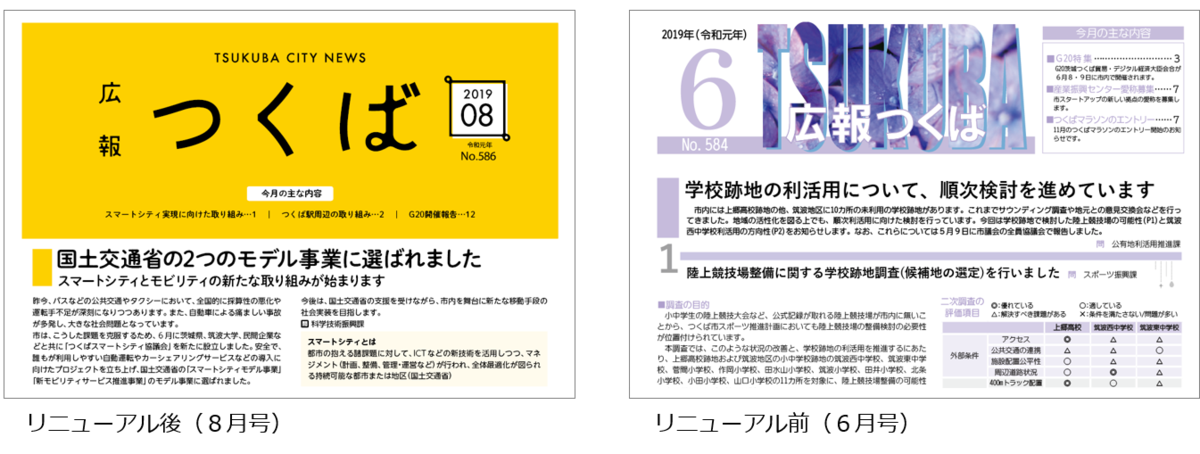
シンプルなデザイン、文字の読みやすさ、カラーユニバーサルデザインに配慮してリニューアルされた「広報つくば」
つくば市は「広報つくば」の紙面デザインを、令和元年(2019年)8月号から刷新したことを2019年7月29日に発表した。
ユニバーサルデザインへの配慮を改善したほか、市政情報をより視覚的に伝える工夫をしている。紙面のサイズ(タブロイド版)に変更はない。
「広報つくば」リニューアルの主なポイント
〇表紙デザインの一新
フリーペーパーや雑誌等のタイトルデザインを参考に、シンプルなデザインに変更。初めて読まれる人や、学生など若年層にも読んでもらえるよう配慮していく。
〇ユニバーサルデザインフォントの導入
字が小さい、読みにくいとの意見を踏まえ、小さな文字でも読みやすく、学習障害(LD)の子どもたちへの対応のひとつとして、自治体や教育現場等での導入が進んでいるユニバーサルデザインフォント(UDフォント)を新たに採用。ユニバーサルデザインフォントにはモリサワのUDフォントが採用されている。
令和元年(2019年)8月号をざっとみたところ、モリサワのUD新ゴと秀英体の丸ゴが使われていた。
〇カラーユニバーサルデザインへの配慮
多様な色覚に対応し、色弱者の方でも見出しやグラフ、図表などが理解でき、見やすいようデザインに配慮している。